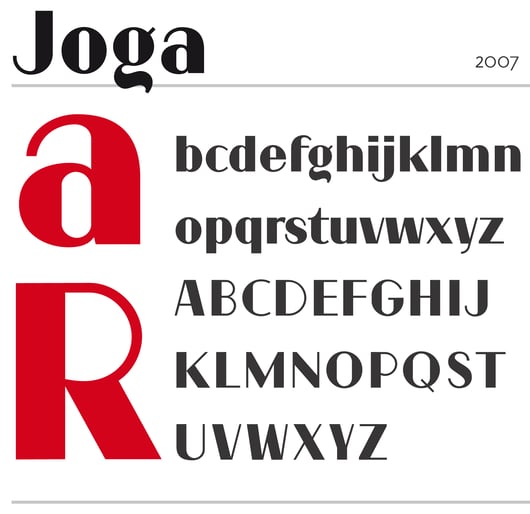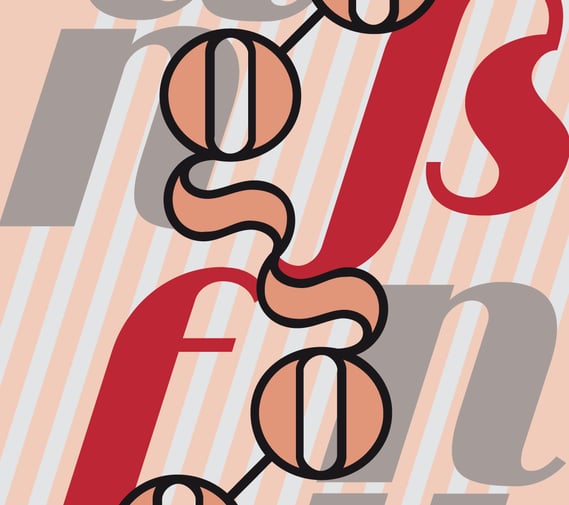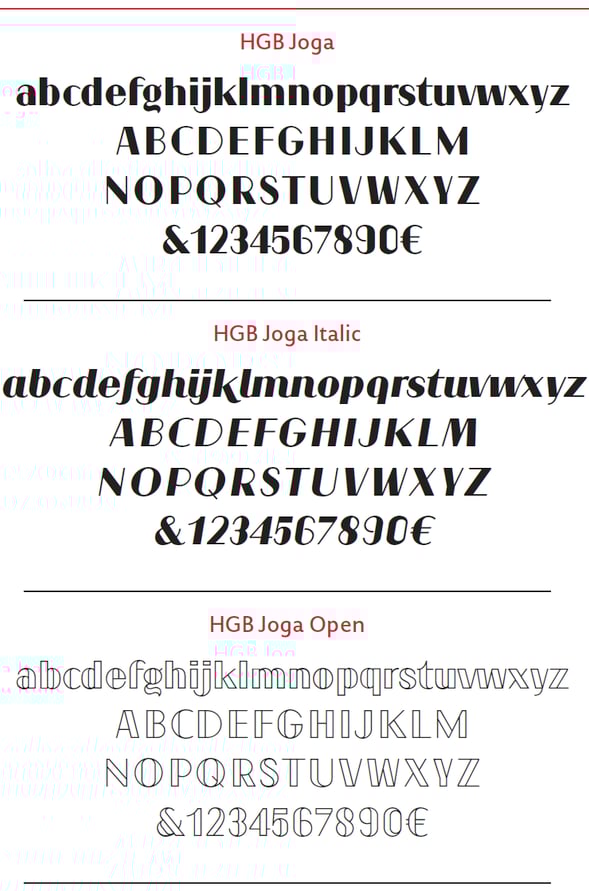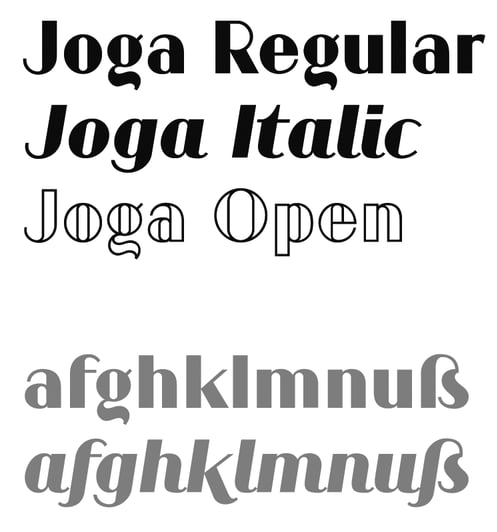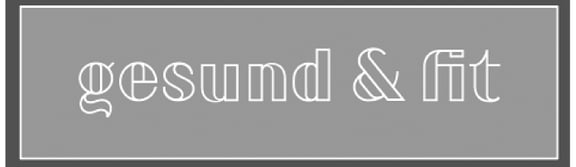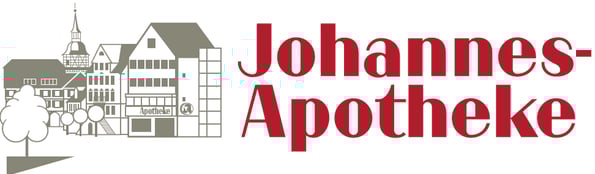
Joga
Die Johannes-Apotheke in Backnang hat seit vielen Jahren eine Leuchtschrift, die in den siebziger Jahren extra für diesen Zweck gezeichnet wurde. Für neue Briefbogen wünschte sich der Apotheker eine ähnliche Schrift, und so zeichnete ich die nötigen Buchstaben im Stil der 70er-Jahre. Wieder einmal konnte ich nicht aufhören, nachdem der Auftrag abgeschlossen war. also kamen die fehlenden Zeichen nach und nach dazu. Der Versuch mit einer schrägen Version führte schließlich zu einer richtigen Kursive mit vielen eigenen Formen. 2015 kam die »Open« dazu, weil neue Leuchtschilder hergestellt werden sollten. Technisch war hierfür eine gefräste Kontur notwendig. 2018 wurde die ursprüngliche Leuchtschrift durch meinen Schriftzug ersetzt.